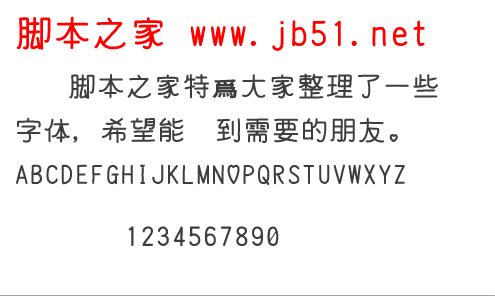
猫猫朋友体(日文名:にゃしぃフレンズ)是一款镶嵌着可爱心形的免费商用日系手写字体。这款字体就像游戏《艦隊これくしょん -艦これ-》中的道具“二周年纪念卷轴”上的字体的感觉。为了不出意外,这款猫猫朋友体是一个字一个字精心制作而成的。这款字体各种各样的文字、记号都沾满了心形,充满活力、温柔、开朗的气氛,我很喜欢这个字体。 虽然这是一款日本设计师制作的字体,但是所包含的中文字型还算比较多的。其中含JIS第1水准2965字,第2水准6355字+IMB扩张字体+日本教育汉字等,约6900个中文字。而且是可以免费商用无限制。适合应用于艺术设计、平面宣传设计、网页设计,书法字帖等领域。